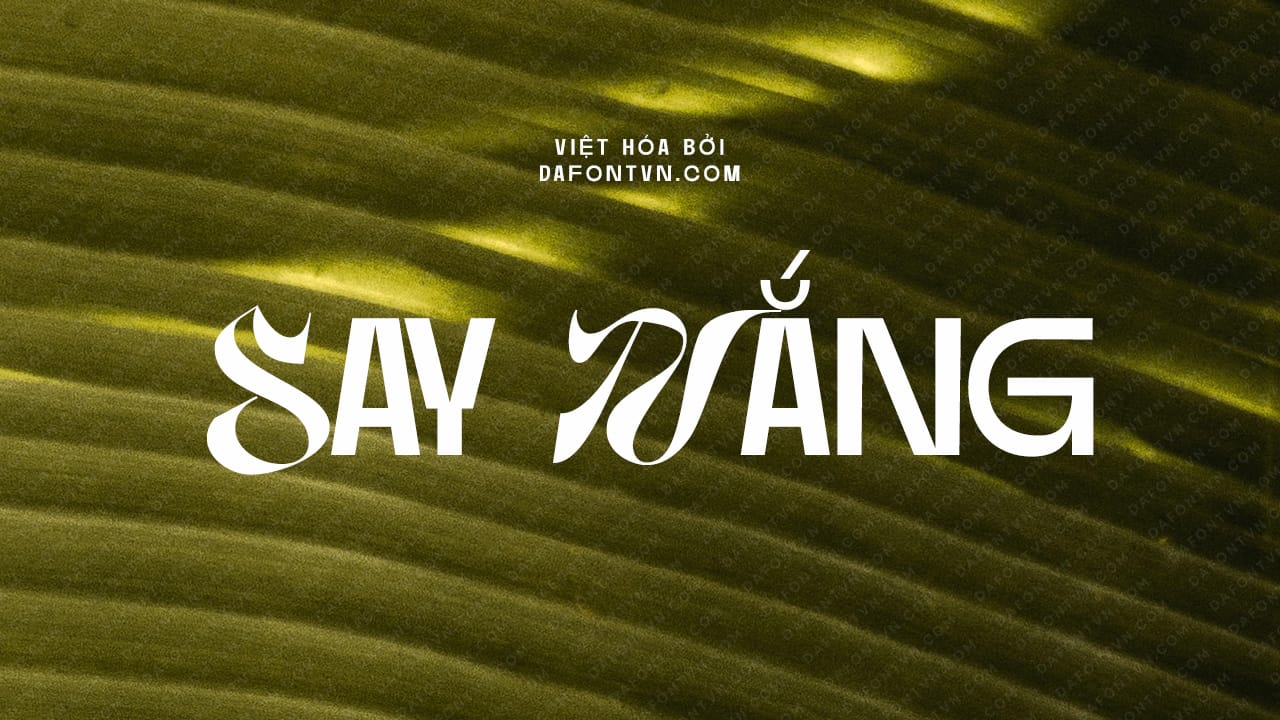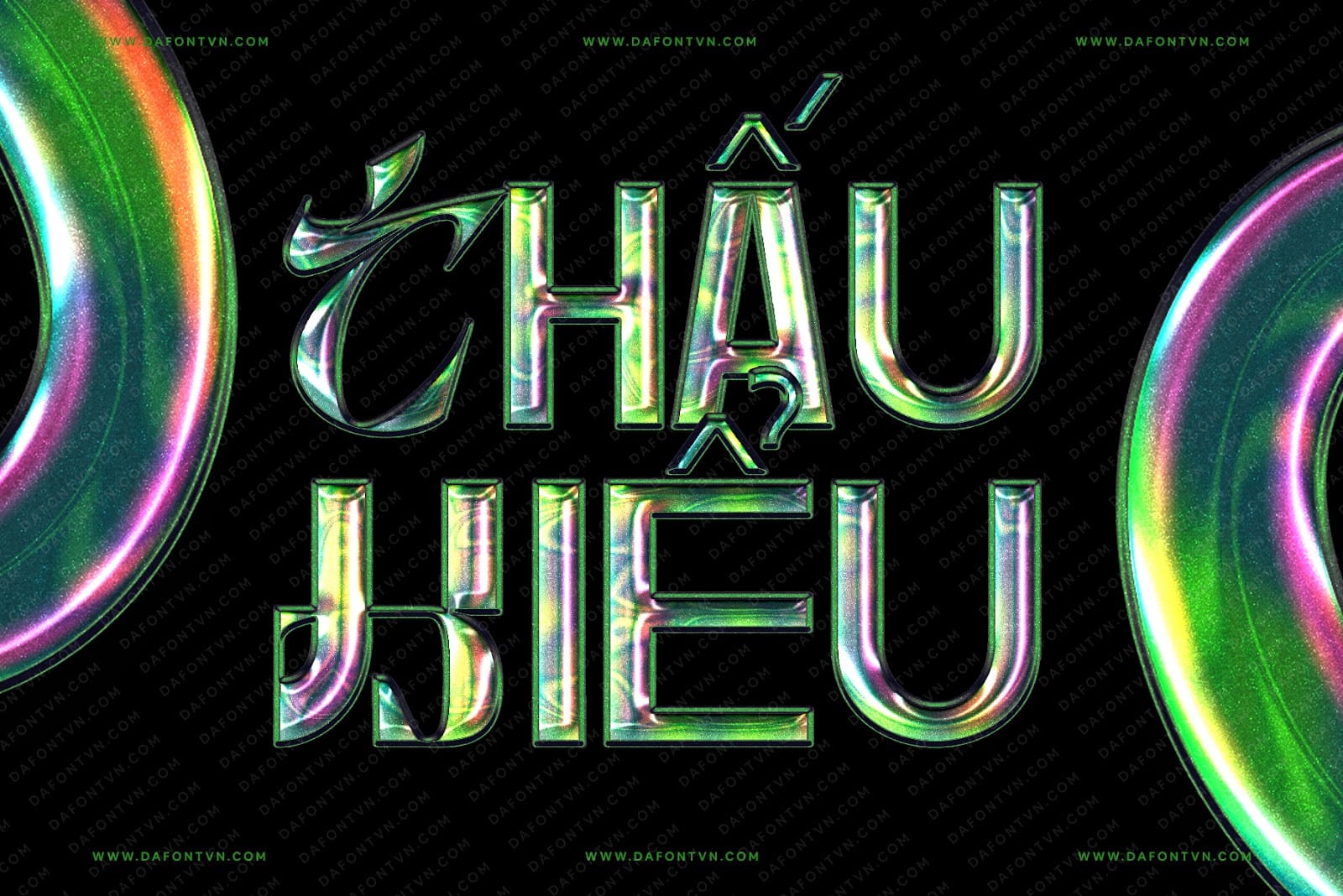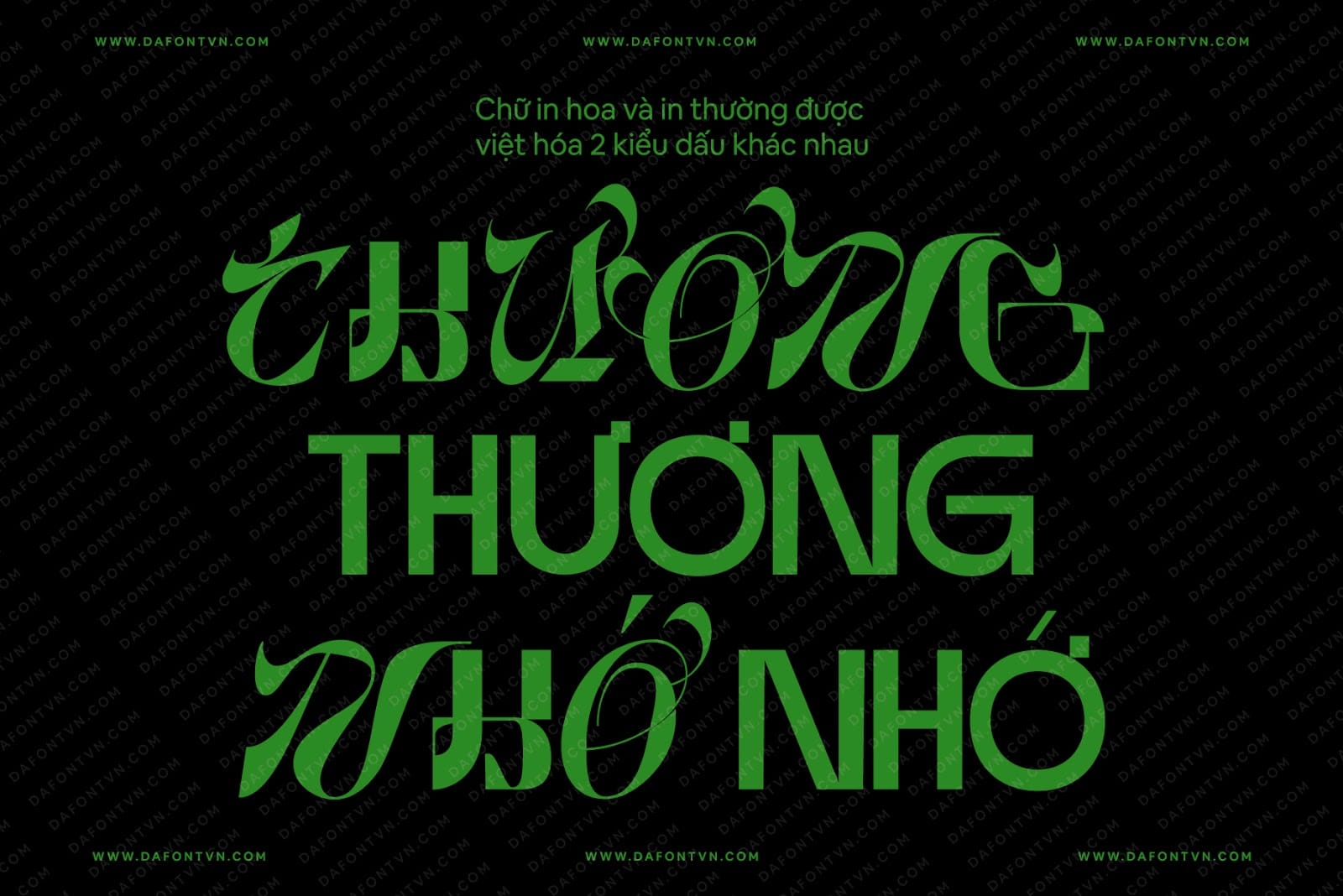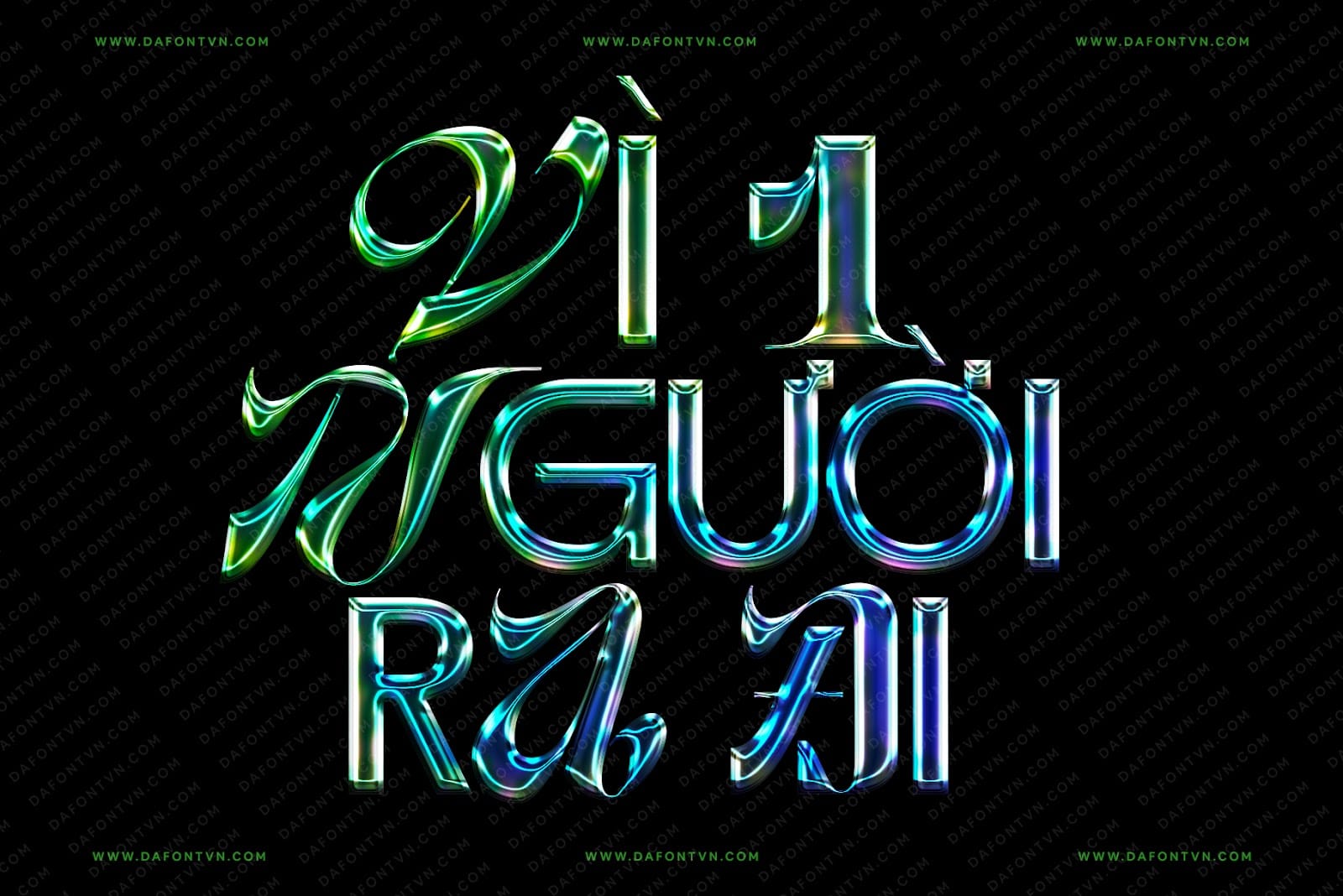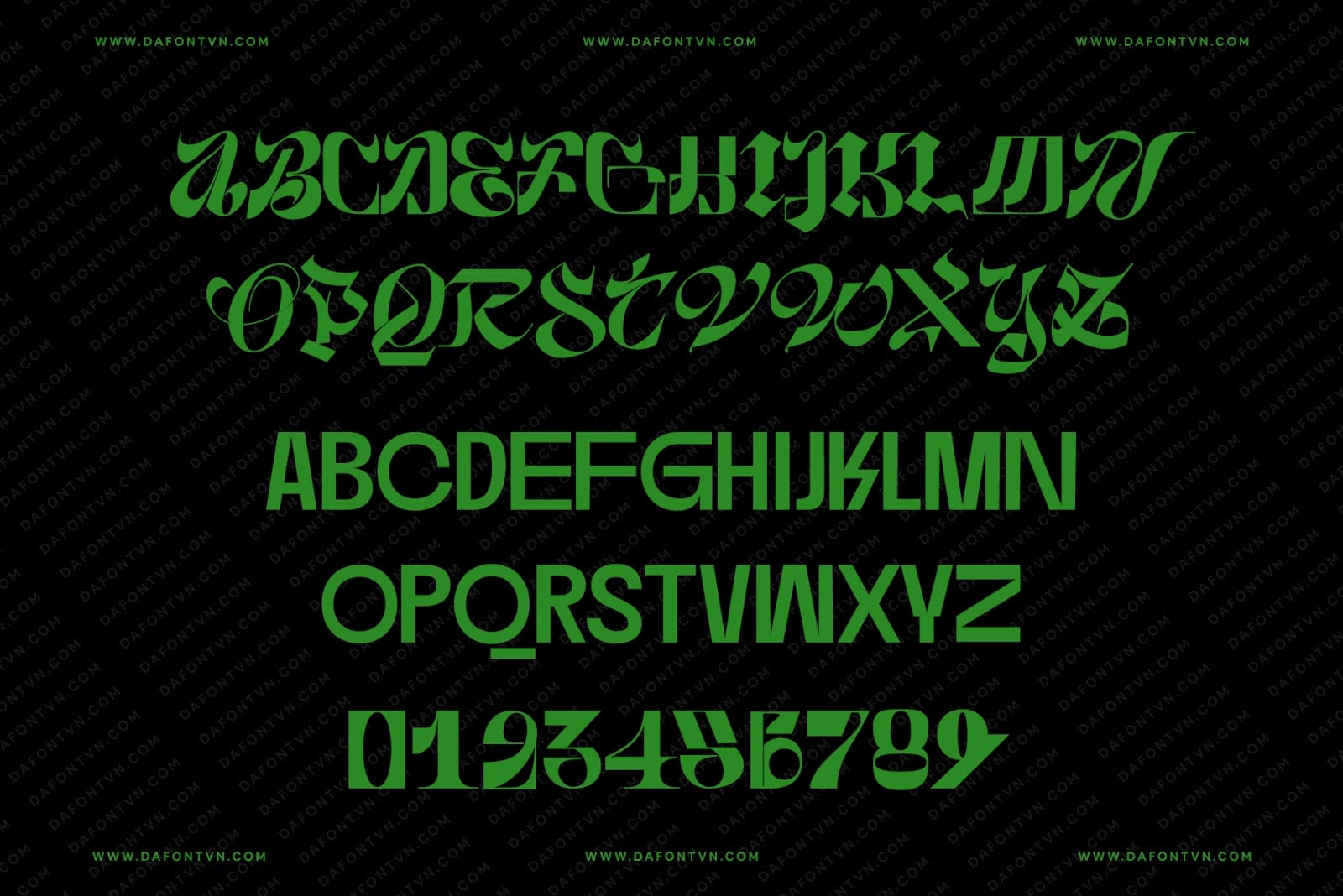
Font 36Daysoftype Việt hóa – Độc đáo, lạ mắt
36Daysoftype là font khá độc đáo được thiết kế bởi Dirtyline Studio và được sử dụng miễn phí cho mục đích cá nhân và thương mại.
Đây là một kiểu font khá đẹp và lạ mắt với ký tự in hoa và ký tự in thường được thiết kế khác nhau vì vậy bạn có thể kết hợp chúng để tạo ra những thiết kế độc đáo. Vì có 2 kiểu khác nhau nên mình đã việt hóa 2 kiểu dấu cho ký tự thường và hoa để nhìn phù hợp hơn.
Ngoài ra, mình đã thêm các ký tự “O” (ss01) và loại bỏ đường viền uốn cong để có thể dễ dàng sử dụng và kết hợp font chữ cho đẹp hơn. Bạn có thể sử dụng các ký tự này từ bảng Glyph.